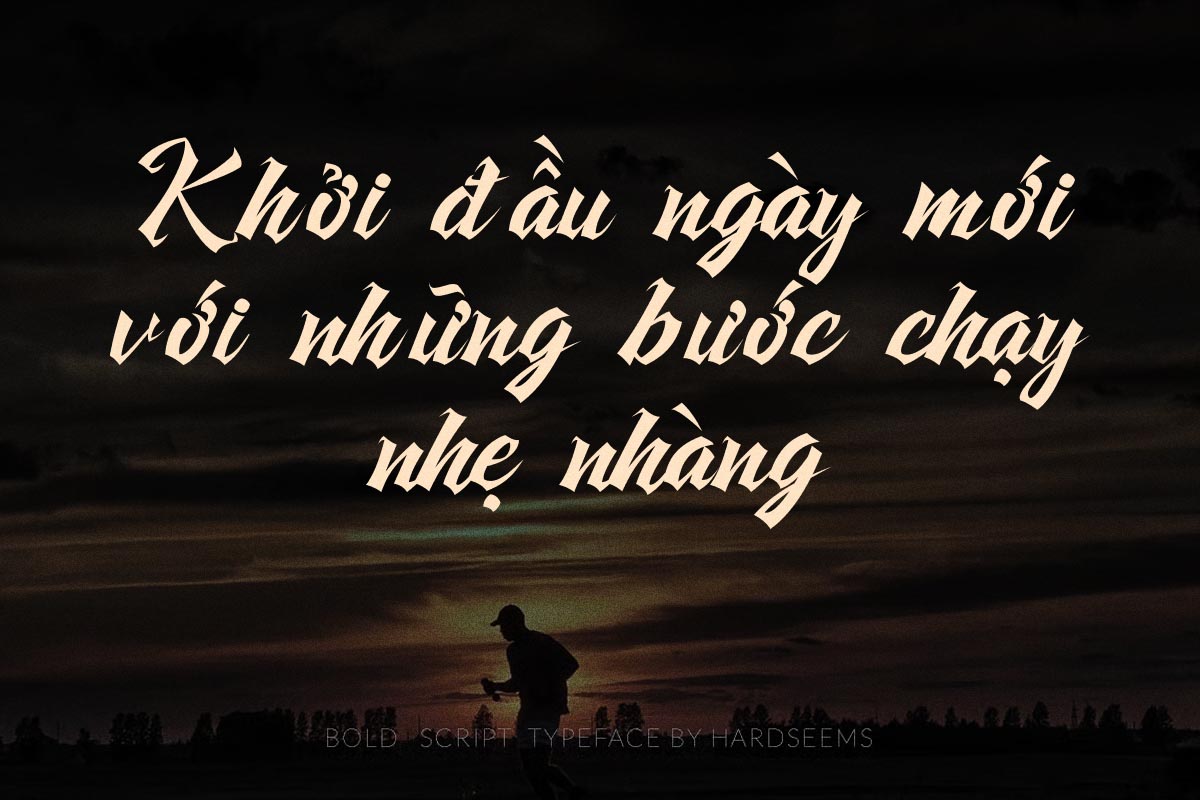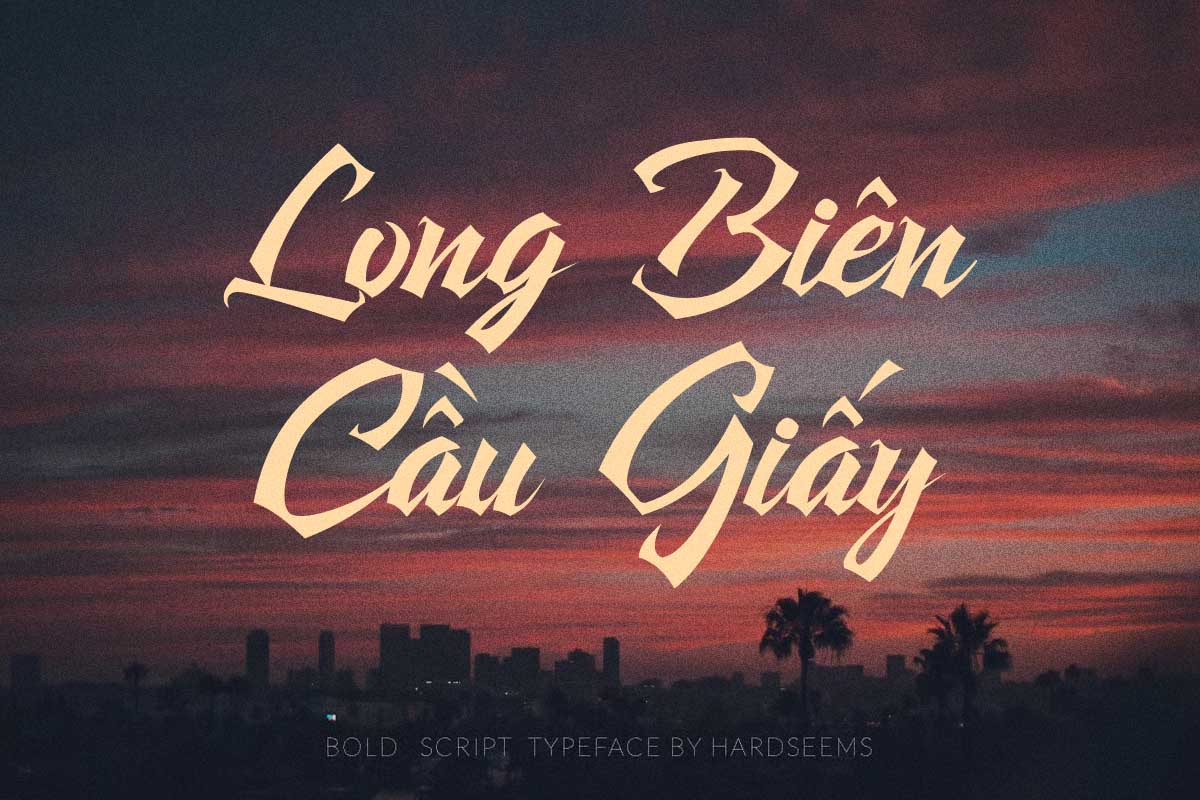
Font chữ đậm phong cách retro mạnh mẽ TH Acttime Việt hóa
TH Acttime là font chữ script đậm ấn tượng, mang phong cách retro – thể thao – phiêu lưu đầy cá tính. Đây là phiên bản Việt hóa được Phạm Sơn thực hiện tỉ mỉ, giúp font hỗ trợ hoàn chỉnh tiếng Việt với dấu chuẩn, giữ nguyên tinh thần mạnh mẽ và uy lực của bản gốc từ Hardseems.
Với thiết kế nét chữ dày, nghiêng nhẹ và dứt khoát, TH Acttime mang cảm giác năng động, mạnh mẽ nhưng vẫn mềm mại, uyển chuyển. Các ký tự được tạo hình sắc sảo, có đuôi kéo dài và phần đầu chữ được vát góc đặc trưng, mang lại vẻ đẹp hoài cổ pha hiện đại, rất phù hợp cho các dự án cần sự ấn tượng và nam tính như thể thao, phiêu lưu, du lịch, streetwear hoặc thương hiệu năng động.
Không chỉ là một kiểu chữ, TH Acttime còn là “dấu ấn cá tính” giúp truyền tải tinh thần tự do, khám phá và chinh phục. Khi được sử dụng trong logo, tiêu đề, poster, banner hoặc bìa tạp chí, font này tạo ra sức hút mạnh mẽ, giúp thông điệp trở nên sống động và dễ ghi nhớ.
Phiên bản Việt hóa của Phạm Sơn đảm bảo các dấu tiếng Việt hiển thị chuẩn, cân đối, tối ưu kerning và độ tương phản giữa các nét, mang đến trải nghiệm trọn vẹn cho người thiết kế. Nhờ đó, TH Acttime trở thành lựa chọn lý tưởng cho những ai muốn kết hợp tính nghệ thuật và hiệu quả thị giác cao trong cùng một font chữ.